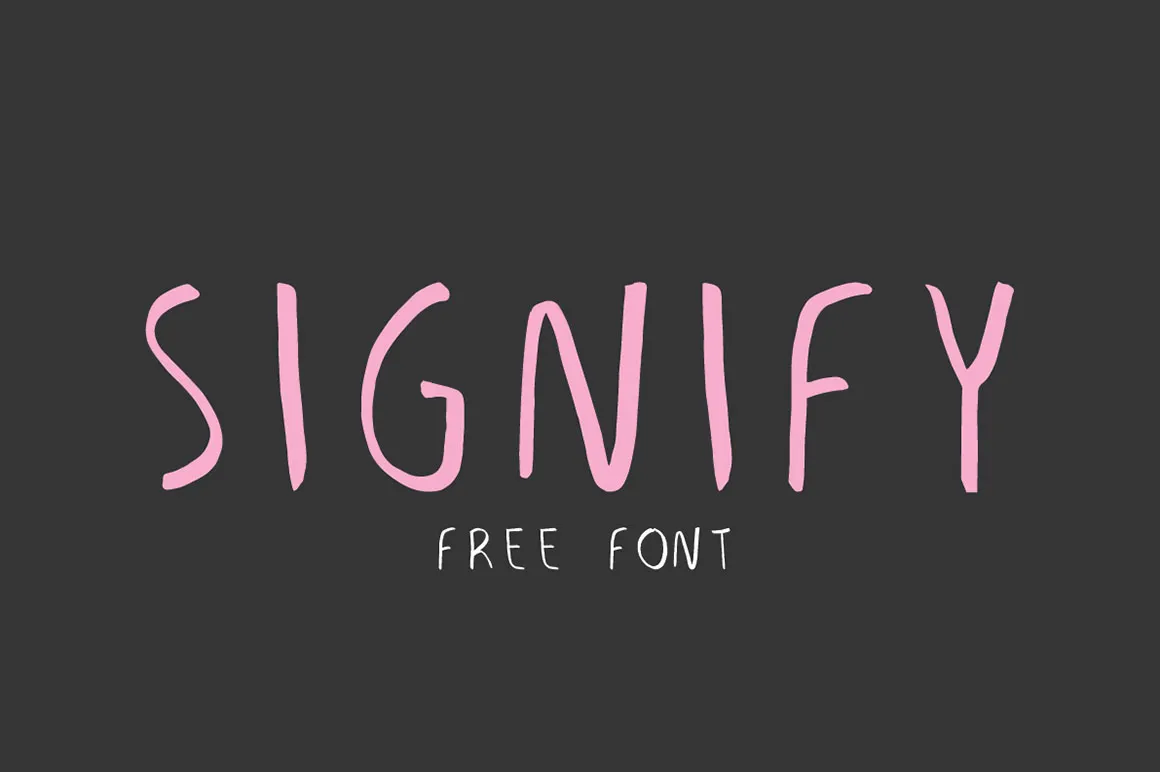
Signify Handmade Font
A fonte ‘Signify Handmade Font’ é uma elegante escolha para os projetos mais criativos e artísticos. Desenvolvida pelo designer Hamilton, esta custom font feita à mão carrega um toque único de arte manual que se tornou versátil o suficiente para dar vida a diversos estilos de design. Seja você um jovem artista ou designer experimentando novas ideias, ‘Signify Handmade Font’ oferece uma maneira prazerosa e divertida de expressar suas ideias ao adicionar personalidade a qualquer projeto. Aproveite o download desta fonte playfully customizada e faça seu trabalho brilhar ainda mais.